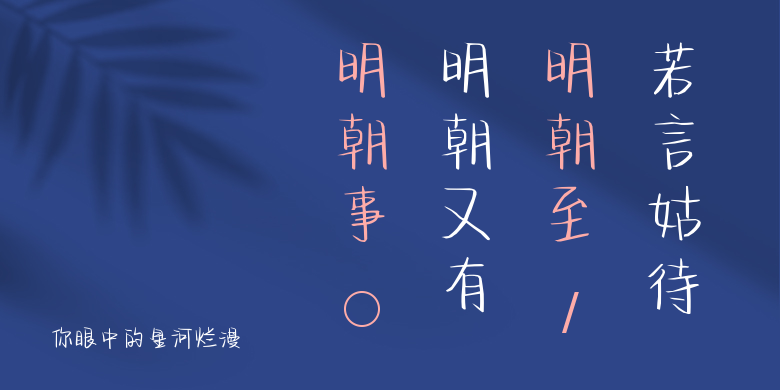
你眼中的星河烂漫
你眼中的星河烂漫,这款字体结构工整、笔画清晰,兼顾美观与易读性,适用于标题、正文、海报、包装、LOGO 等多种场景。字形优雅稳定,风格百搭耐看,适配日常排版与创意设计,让文字呈现更舒适、更具质感。你眼中的星河烂漫一笔一画,皆是细节,以均衡的比例、流畅的线条打造舒适视觉体验,字形端正大气,风格简约现代。无论是商业设计、品牌宣传还是日常排版,都能轻松驾驭,让文字更有格调与力量。你眼中的星河烂漫字体下载。